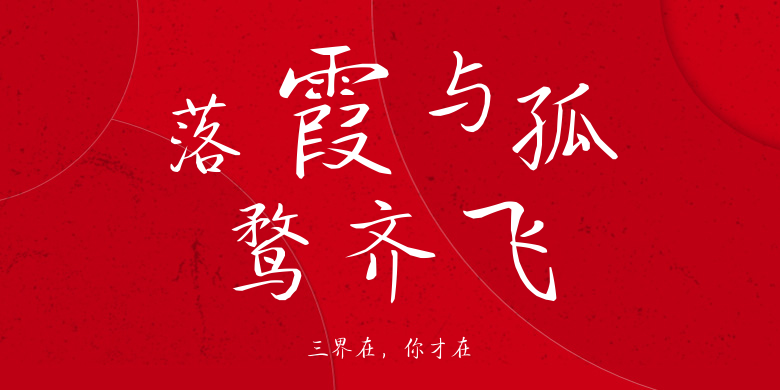
三界在,你才在
三界在,你才在,这款字体结构工整、笔画清晰,兼顾美观与易读性,适用于标题、正文、海报、包装、LOGO 等多种场景。字形优雅稳定,风格百搭耐看,适配日常排版与创意设计,让文字呈现更舒适、更具质感。三界在,你才在一笔一画,皆是细节,以均衡的比例、流畅的线条打造舒适视觉体验,字形端正大气,风格简约现代。无论是商业设计、品牌宣传还是日常排版,都能轻松驾驭,让文字更有格调与力量。三界在,你才在字体下载。